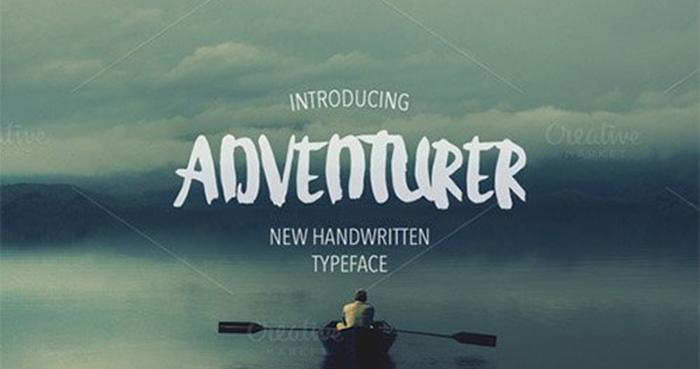
Adventurer Handwritten Font – Download Grátis
A Adventurer é uma fonte escrita a mão casual com traços brush, perfeita para criar identidades de logomarca, citações impressas, cartões de convite de casamento, cabeçalhos de mídia social, embalagens de produtos e muito mais. Inspirada em letras manuscritas reais que transmitem uma sensação de casualidade perfeita para criar um visual único. Perfumada com sua elegante aparência deslizante, a Adventurer é o tipo de fonte que pode transformar qualquer projeto digitado em algo extraordinário. É ideal tanto para trabalhos profissionais quanto para expressões mais pessoais e criativas. Seja você um designer gráfico ou uma pessoa buscando criar identidades visuais única em seu trabalho pessoal, a Adventurer está aqui para adicionar aquela pequena diferença que faz toda a diferença.